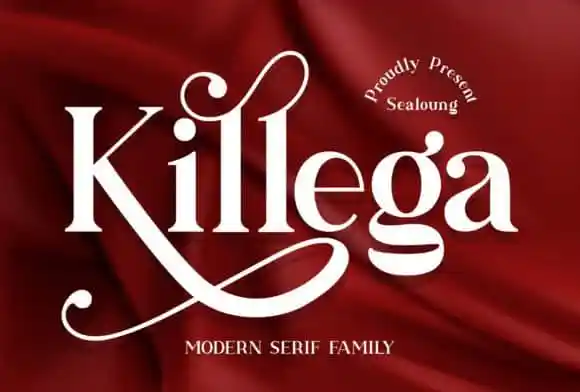
Killega Serif Font – Download Grátis
Descubra a elegância e sofisticação do Killega Serif Font ao criar projetos memoráveis. Essa tipografia cuidadosamente criada garante uma qualidade premium, transmitindo um senso de luxo. O designer Sealoung introduziu várias alternativas de caracteres serif em seu trabalho meticuloso, fazendo deste tipo font único e destacando-o dos mais comuns títulos sans-serif. Elegante e cuidadosamente produzido para se tornar a escolha número um, este tipo de font tem o potencial de levar seus ideias criativas ao ponto máximo. Adquira agora a Killega Serif Font e deixe seu projeto brilhar ainda mais.